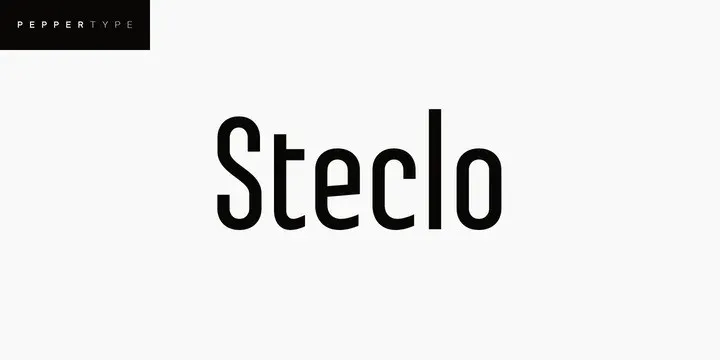
Steclo Sans Serif é uma tipografia sem serif clássica e duradoura que abrange os 9 pesos desde Espinho (light) até Escuro (black), bem como as itálicas obliqüas para cada um desses pesos. Este é o trabalho do designer Pepper Type, conhecido por criar fontes com personalidade e carácter técnico acentuado. Steclo não apenas oferece uma linguagem de suporte rica que inclui sets gílitos pan-europeus latinos e básicos do alfabeto cirílico, mas também incorpora seu design em um estilo de exibição sem-serif. Essa fonte é perfeita para situações que exigem clareza visual, como portais e sites corporativos modernos ou aplicações tecnológicas onde a simplicidade do design combina bem com a eficiência da função. Com uma aparência elegante e versátil, Steclo é um ótimo complemento para seu projeto em desenvolvimento.